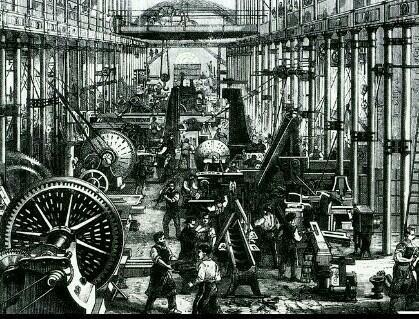
Se puede afirmar que el papel se inventó en el año 105 d.C. por Cai Lun, esto impulso la escritura en este nuevo material
Existe una fecha clave, 1440 es el año en el que por fin se atribuye de manera oficial la invención de la imprenta al alemán Johannes Gutenberg. Con este invento la escritura se hacia uniforme y estilizada en varios medios.
A principios del siglo XVI el célebre Aldo Manuzio, que fundó la imprenta Aldina en Venecia, trabajó grabando diferentes tipos griegos, romanos, hebreros y las primeras itálicas para sus ediciones.A partir de su trabajo empieza lo que denominamos época de oro de la tipografía francesa. En toda Europa el auge de la tipografía se establece y empiezan a surgir grandes tipógrafos, como Claude Garamond.
La revolución continuó con la llegada de la Era Industrial, que supuso un cambio dramático en las artes gráficas y la tipografía. Los delicados tipos artísticos del pasado tuvieron en los tipos mecánicos, gruesos y rígidos, una gran competencia. Los dueños de periódicos los empezaron a usar para los titulares de gran puntaje, capaces de llamar más la atención. Joseph Jackson, Thomas Cottrell y Vincent Figgins fueron sus principales exponentes,
Y a partir de 1800 otra innovación tecnológica importante fue el tipo sans serif, que si bien había aparecido en un catálogo publicado por William Caslon IV en 1816, no causó impacto hasta tiempo después. Criticadas al comienzo por su simpleza, tuvieron diferentes nombres (góticas americanas, sansurryphs, grotescas, dóricas), pero terminaron imponiéndose gracias a su alta legibilidad.
Theodore Low De Vinne mandó a realizar a finales del siglo XIX un tipo especial para la impresión de la revista Century, el primero diseñado especialmente para una publicación. Desde entonces, buscar modelos especiales o más de un modelo especial para darle una identidad a las publicaciones se volvió una costumbre. Con los avances en las Monotype, el arte de la tipografía y la impresión, los talleres y los artistas caligráficos, la maduración de las familias tipográficas.